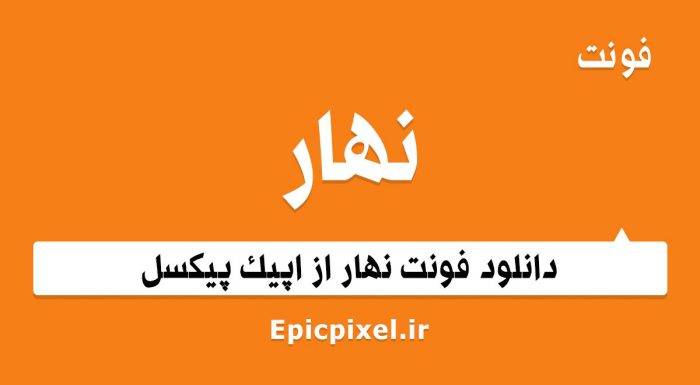
3 فونت نهار فارسی
فونت فارسی نهار، با طراحی خاص و منحصربه فرد خود، گزینه ای ایده آل برای طراحانی است که به دنبال ایجاد تمایز در آثارشان هستند. این فونت با ساختار هندسی دقیق و خطوط نرم، ترکیبی چشم نواز از مدرنیته و اصالت را به نمایش می گذارد. در طراحی فونت نهار، به خوانایی متن در اندازه های مختلف توجه ویژه ای شده است؛ به همین دلیل، هم در عناوین بزرگ و هم در متون کوتاه، به خوبی قابل استفاده است.
یکی از ویژگی های برجسته فونت نهار، تنوع در وزن های آن است که به طراحان امکان می دهد با انتخاب وزن مناسب، حس و حال موردنظر خود را به مخاطب منتقل کنند. این تنوع، دست طراح را در ایجاد طرح های گوناگون، از پوستر و لوگو گرفته تا طراحی وب سایت و بسته بندی، باز می گذارد. بااین حال، باید توجه داشت که استفاده بیش ازحد از این فونت در یک متن ممکن است باعث کاهش تمرکز مخاطب شود؛ بنابراین، توصیه می شود در کنار فونت نهار، از فونت های ساده تر نیز استفاده شود.
فونت نهار با پشتیبانی کامل از زبان فارسی و اعراب، خیال طراحان را از نمایش صحیح متون راحت می کند. این فونت رایگان است و به راحتی می توانید آن را دانلود و در پروژه های خود استفاده کنید. اگر به دنبال فونتی مدرن و درعین حال خوانا هستید که به طرح های شما جلوه ای خاص ببخشد، فونت نهار انتخابی هوشمندانه خواهد بود.